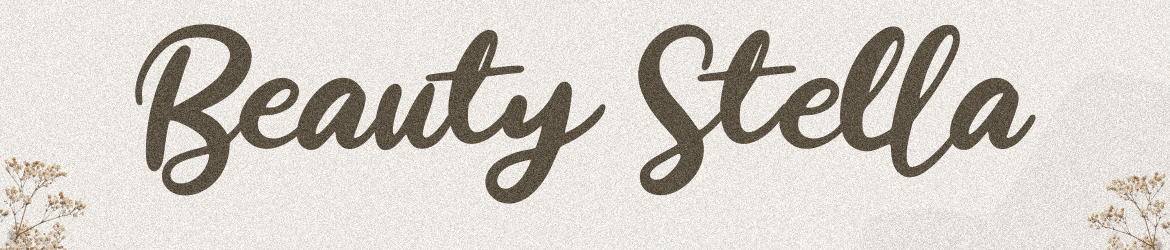
Beauty Stella Font – Fonte Grátis
Beauty Stella Font – Download Grátis
Beauty Stella Font
Esta é uma fonte escrita a mão delicada e elegante, conhecida por transmitir beleza e classe, criada especialmente para aqueles que desejam uma aparência fresca e refinada em seus projetos de design. A fonte ‘Beauty Stella Font’ da Enigma Lettering Studio traz um toque romântico ao seu trabalho, adequando-se perfeitamente a designs que buscam equilíbrio e sofisticação. Perfeita para uso em cartazes publicitários, gráficos de web ou letras de livros, esta fonte escrita a mão suaviza qualquer projeto com sua graça refinada. A Enigma Lettering Studio é uma referência sólida no design de escritas, dedicando-se à criar fontes que se destacam por sua autenticidade e beleza. Para os criadores buscando um toque único e sofisticado para seus projetos, a Beauty Stella Font da Enigma Lettering Studio é uma escolha inspiradora e inovadora.